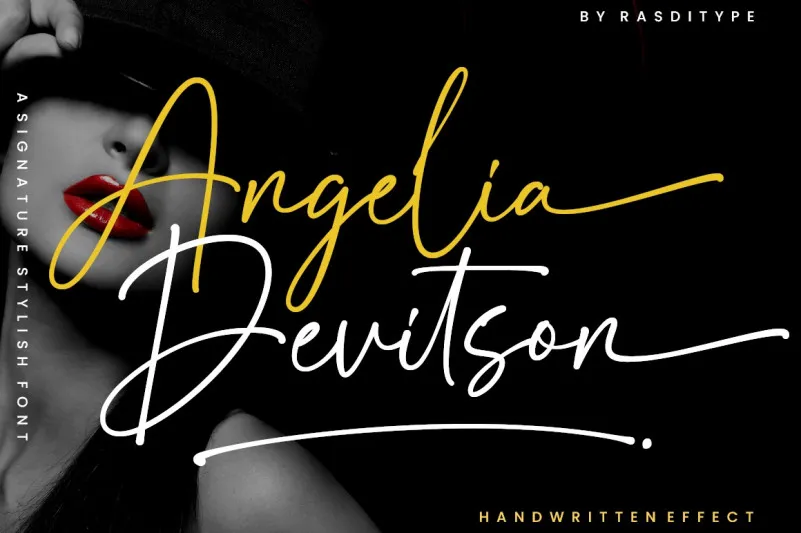
Esta fonte tipográfica é uma bela e simples tipografia criada por RasdiType que expressa elegância e modernidade através do estilo da escrita à mão. Perfeita para estilos de marca, convites, selos, designs de casamento, postagens no Facebook ou Instagram, esta fonte é perfeitamente adaptável a várias necessidades gráficas. Ela possui uma característica PUA (Personal Use Allowed), o que significa que você pode acessar facilmente todos os caracteres e variações em sua documentação. Este tipo de fonte será um complemento ideal para quem busca estilos elegantes e modernos para seus projetos digitais, seja ele para um projeto de marca pessoal ou corporativo, convites para casamentos ou conteúdo online. Com seu design sofisticado e moderno, a Angelia Devitson Font é uma opção perfeita para designers profissionais que buscam adicionar um toque único e sofisticado em suas criações. Seja para criar um logotipo de marca impactante, desenvolver um projeto editorial elegante ou projetar uma assinatura online atrativa, esta fonte vai atender todas as suas necessidades. Ela é a escolha perfeita para quem busca uma combinação única e moderna entre estética e praticidade em suas criações digitais.